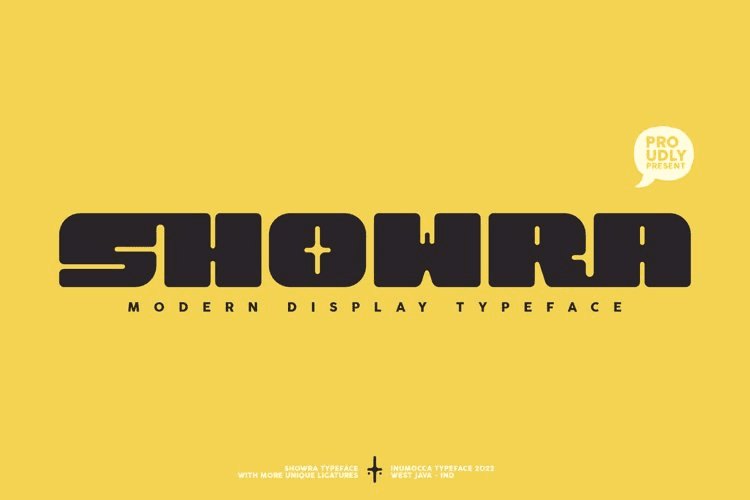
[Fontbundles] Showra Font (2022)
Современный шрифт Showra, смелый и мощный.
И я хочу представить современный и стильный вкус.
Шрифт поставляется с наборами лигатур (более 240) и альтернативами.
Отличный шрифт для использования в вашем проекте,
например, брендинг, название фильма, заголовок письма, обложка книги или содержание книги, обложка журнала, плакат, цитаты, логотипы и другие виды дизайна.